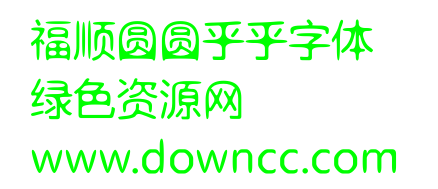
福順圓圓乎乎體
福順圓圓乎乎字體是一款筆觸柔軟溫潤的福順字體,字體辨識度高、深淺度適中,有著極佳的視覺觀賞體驗,無論是用作手機字體還是平面設(shè)計都很不錯,綠色資源網(wǎng)誠意推薦!
福順圓圓乎乎體特色
圓圓乎乎字體有著圓潤的造型,給人一種沒有棱角的柔和感,字體筆畫清晰不潦草,觀賞性極佳,可以讓文字更加容易被閱讀,不會給人有攻擊性的印象體驗!
圓圓乎乎字體